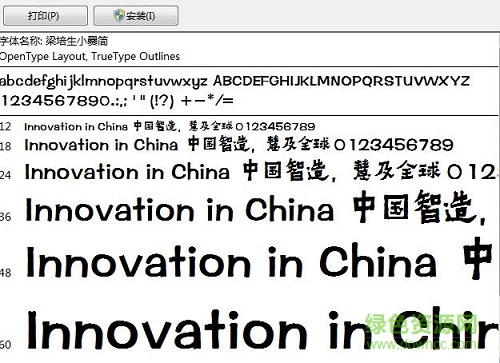
梁培生小爨簡(jiǎn)是一款根據(jù)故爨體字制作而來的電腦字體,該字體筆力雄強(qiáng),結(jié)體茂密,繼承漢碑法度,有隸書遺意,運(yùn)筆方中帶圓,筆畫沉毅雄拔,非常有特色,喜歡可以下載使用!
梁培生小爨簡(jiǎn)是一款獨(dú)具魅力的中文字體,是根據(jù)中國古代稀有字體爨體字打造的代表云南特色的字體,是中國漢字從隸書到楷書的過渡字體。